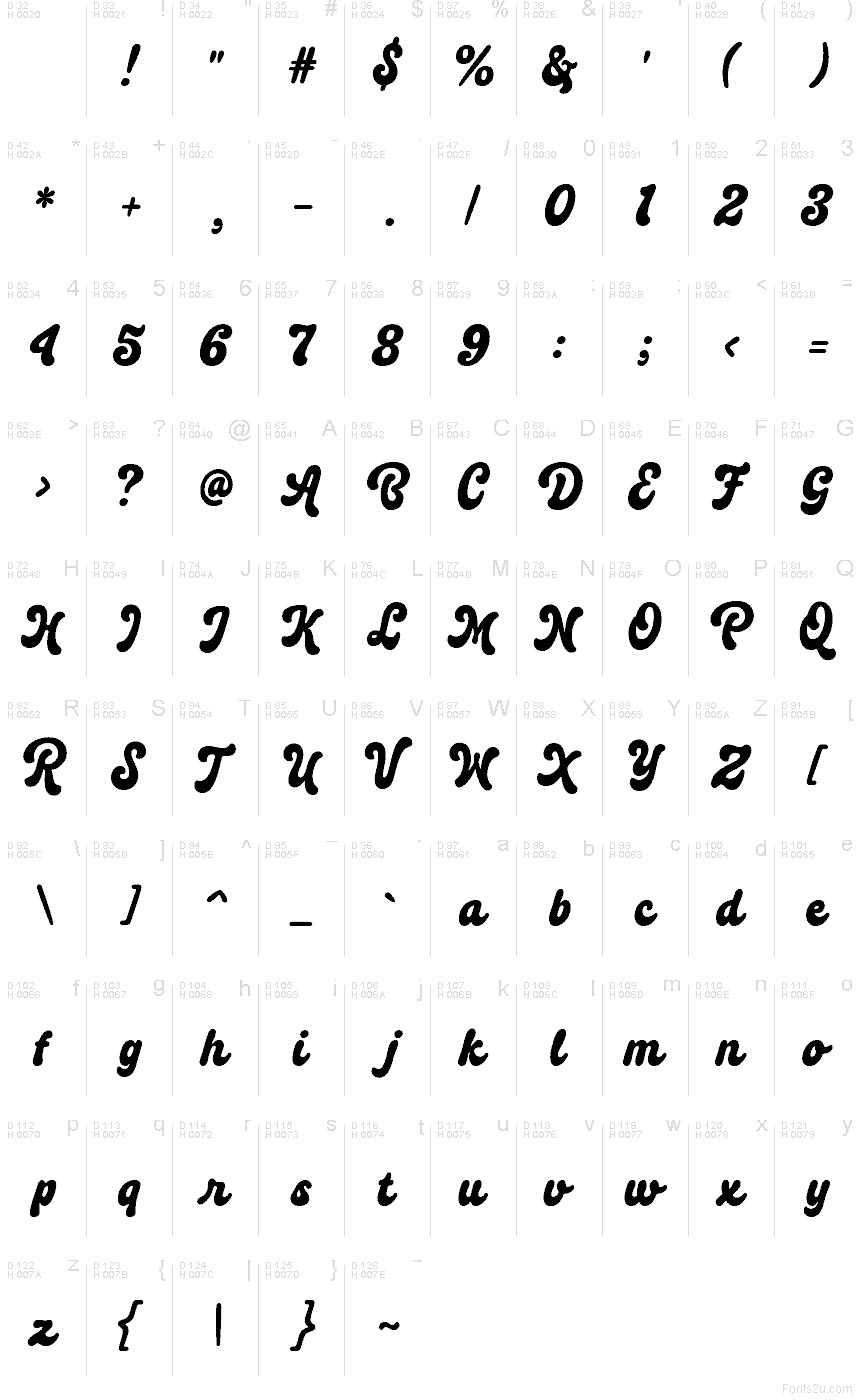
Bright Miracle es una tipografía script retro gratuita creada por Burhan Afif, que captura el estilo redondeado y pintado a mano de los antiguos letreros publicitarios y las letras de heladería. Sus caracteres se sienten llenos y fluidos, con trazos gruesos, uniones suaves y un ritmo vivaz que mantiene un aspecto casual y auténtico en lugar de demasiado pulido.
Esta fuente gratuita es ideal para bocetos de logotipos, packaging de cafeterías, titulares de carteles y títulos para redes sociales, donde una tipografía cálida y nostálgica ayuda a transmitir la atmósfera adecuada. También funciona muy bien para frases cortas de marca y monogramas, ya que sus curvas marcadas y trazos de entrada fluidos dan a incluso unas pocas letras una presencia completa y amistosa.